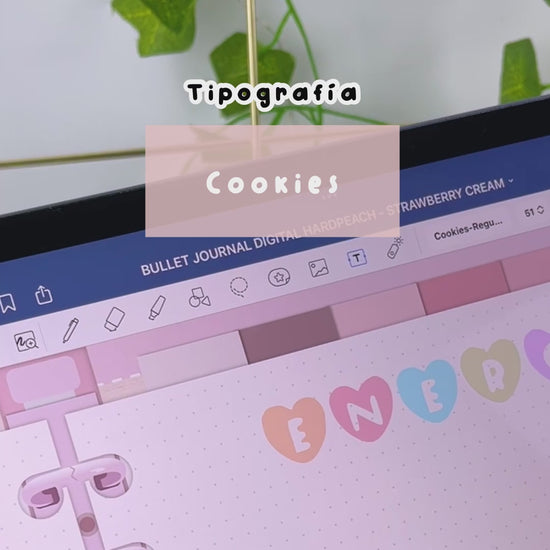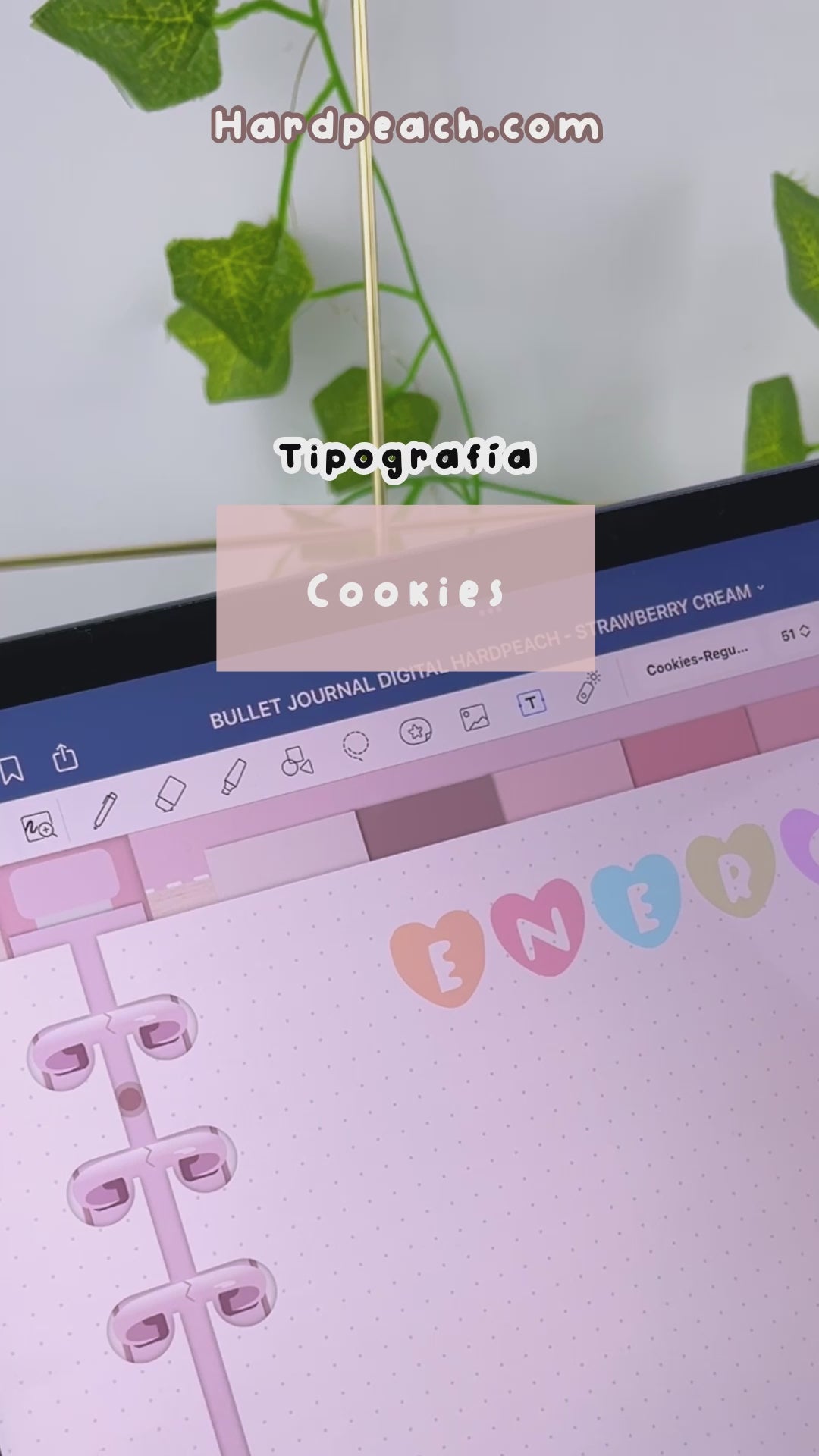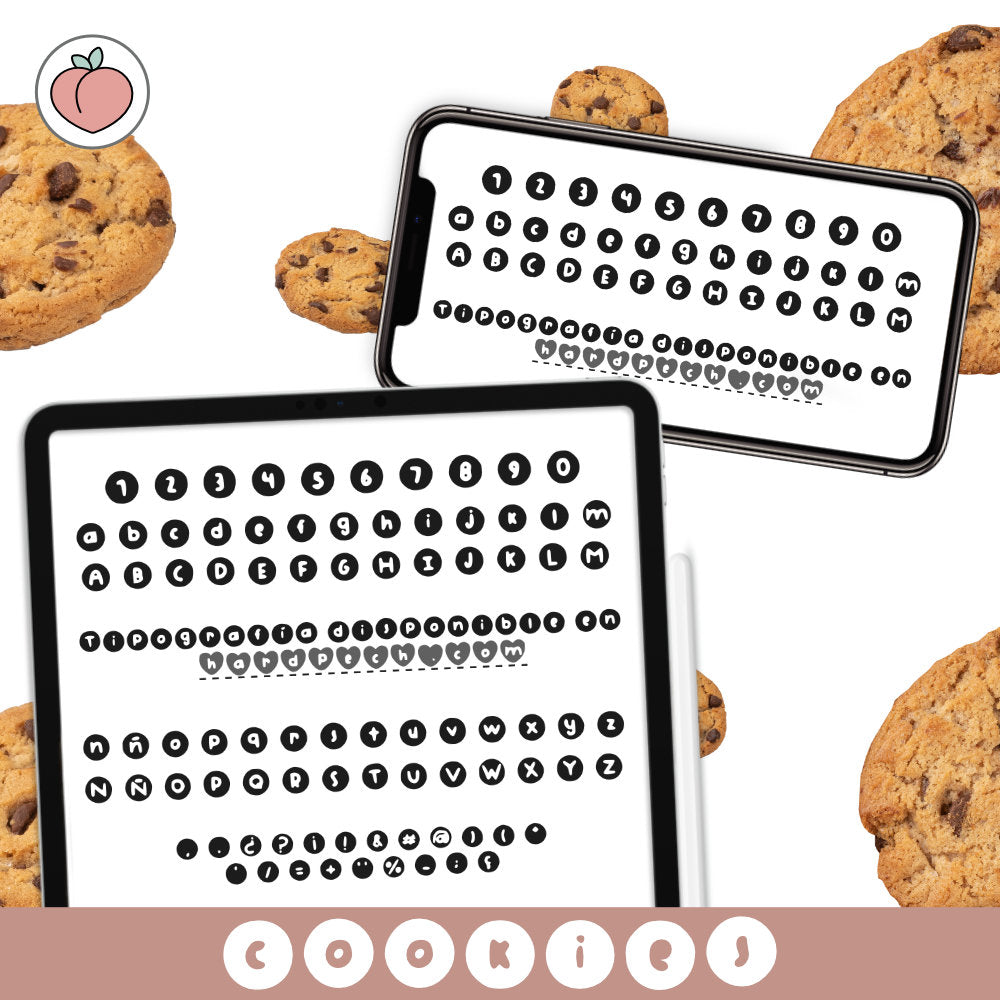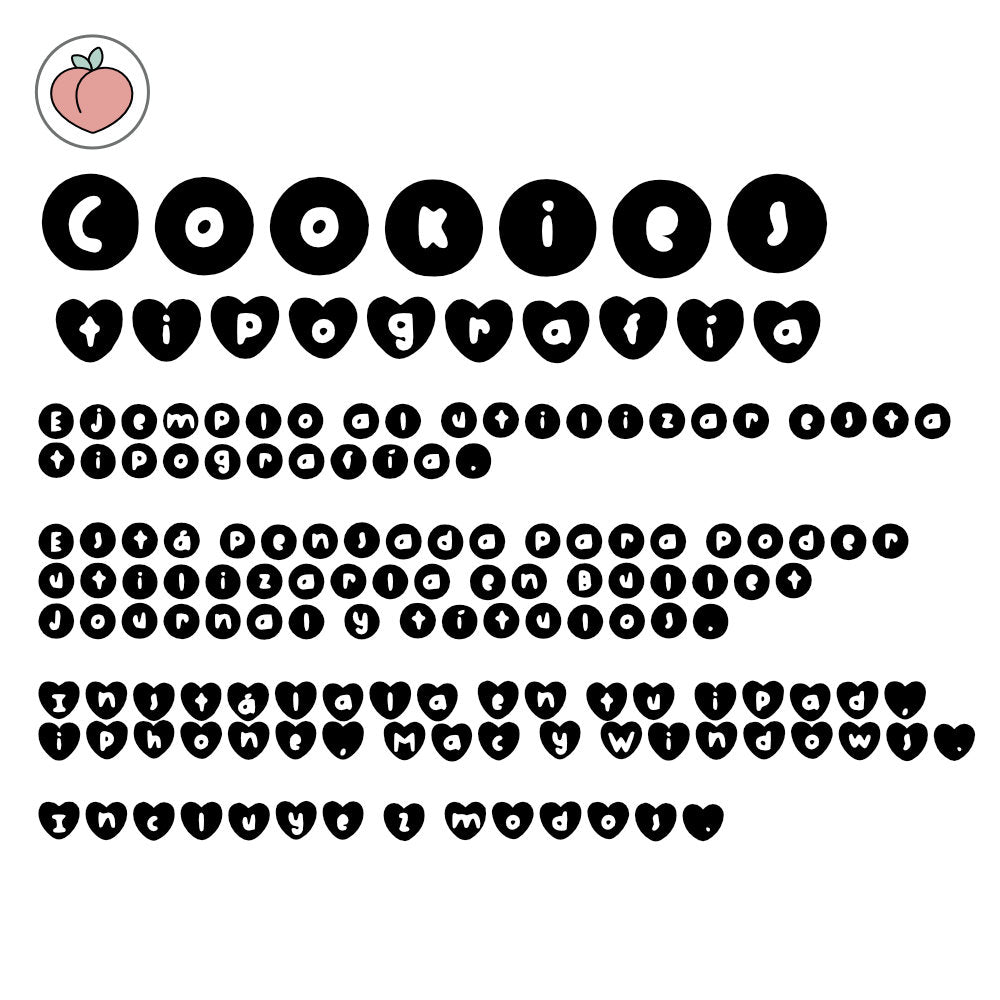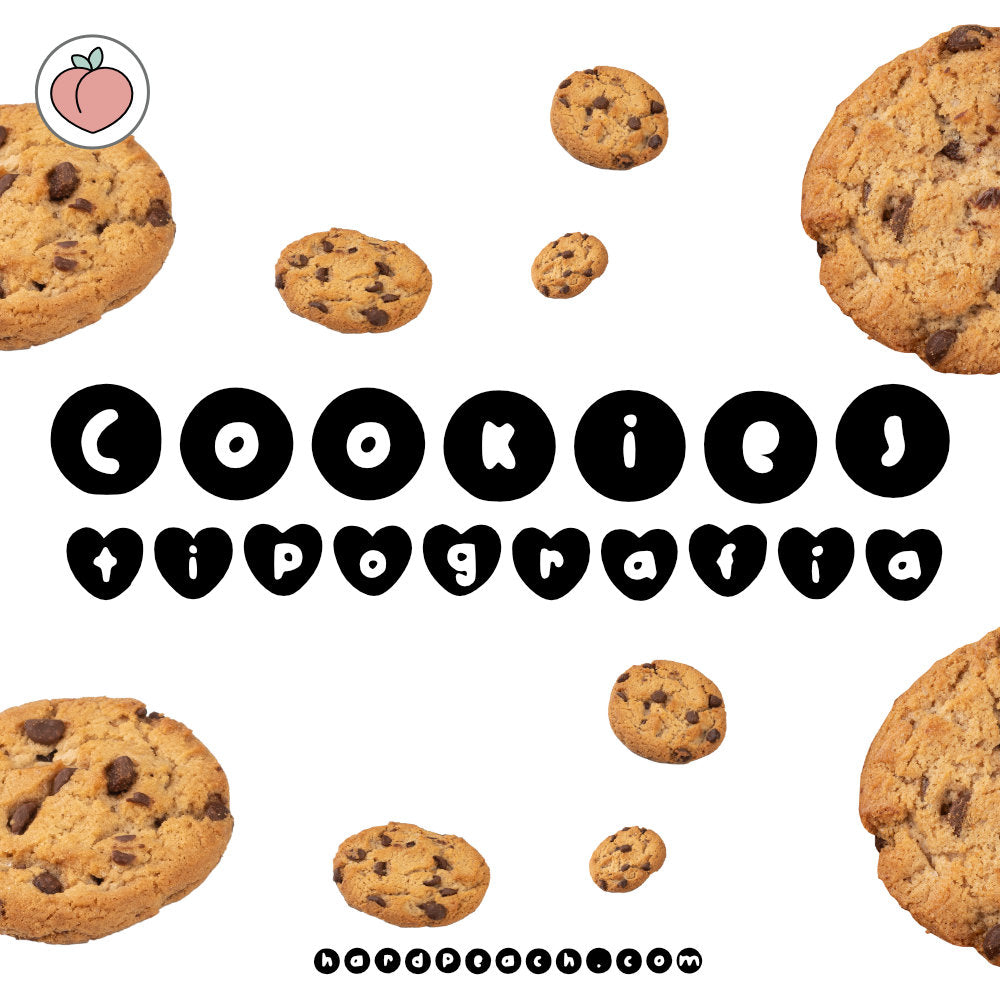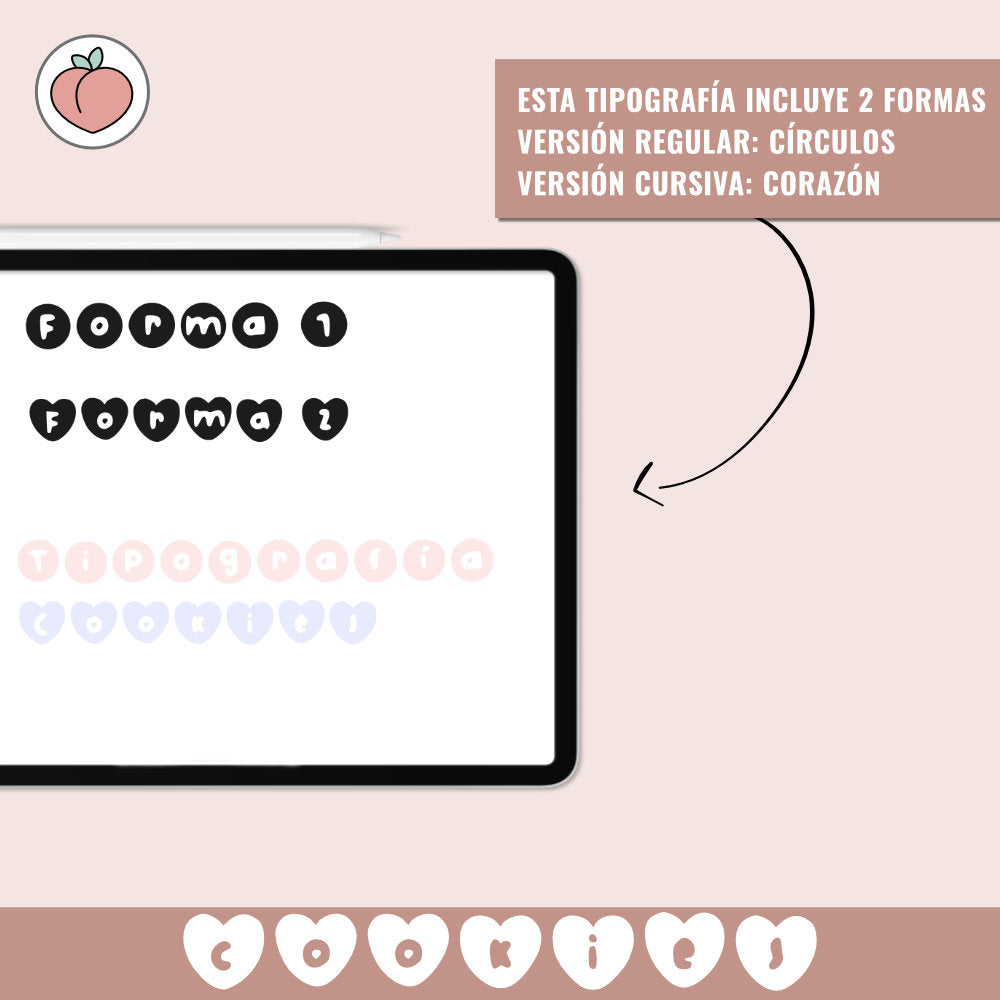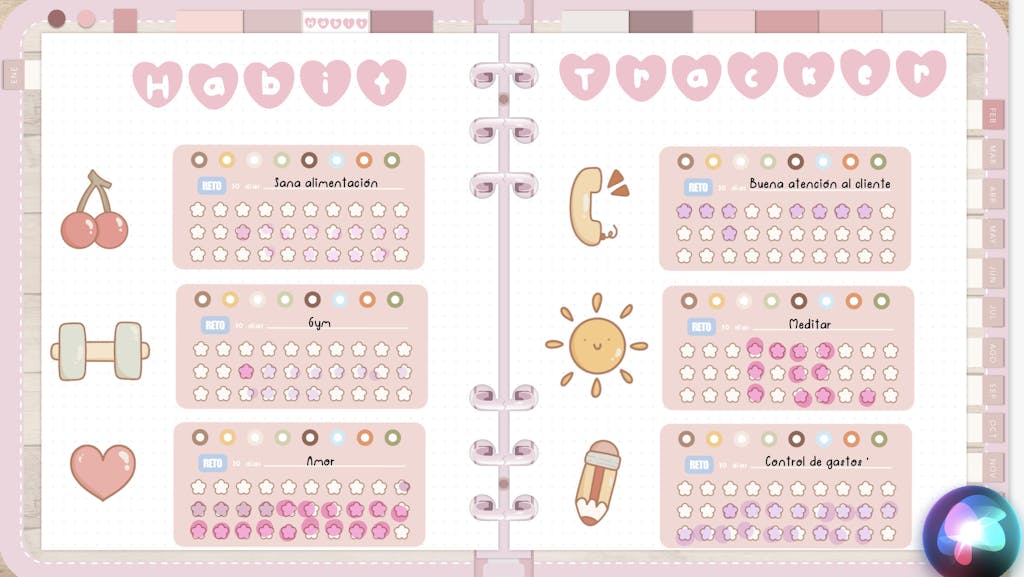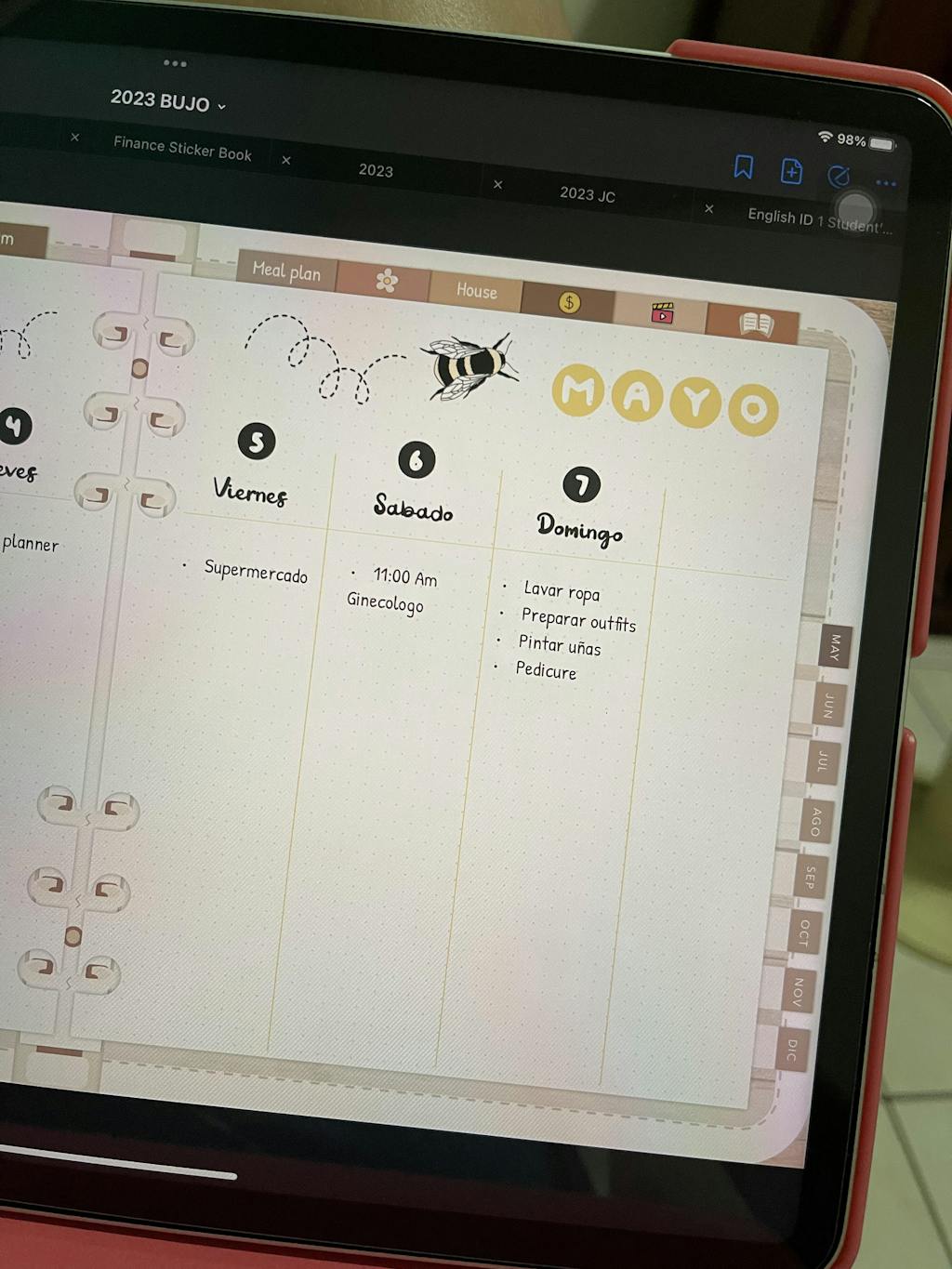
TIPOGRAFÍA COOKIES: Fuente 2 en 1 para títulos, lettering, bullet journals, agendas digitales y proyectos creativos
¡Tipografía 2 en 1 para títulos, Bullet Journal y agendas creativas! ✨
Descubre nuestra tipografía 2 en 1, diseñada para añadir un estilo totalmente único a tus títulos, apuntes, bullet journals, agendas digitales y proyectos creativos. Esta fuente versátil permite escribir con un formato circular o en forma de corazón, dando un toque divertido, moderno y especial a todas tus anotaciones y diseños.
Características principales:
- Dos modos de tipografía: Elige el estilo que mejor se adapte a tu proyecto y personaliza tus textos con facilidad.
- Colores ilimitados: Utiliza la tipografía en el color que necesites para destacar tus títulos, secciones o páginas de tu Bullet Journal y agenda.
- Versatilidad total: Perfecta para apuntes digitales, notas, títulos, encabezados, tarjetas, invitaciones y proyectos de lettering digital.
Ideas de uso:
- Bullet Journals y agendas digitales 🗓️
- Títulos y encabezados para documentos, presentaciones y proyectos ✨
- Notas y apuntes digitales 📝
- Diseños creativos e ilustraciones 🎨
Con esta tipografía 2 en 1, podrás darle vida a tus proyectos y planificaciones, creando un estilo único y atractivo, sin perder funcionalidad ni facilidad de uso. Perfecta para estudiantes, profesionales, amantes del Bullet Journal y cualquier persona que quiera personalizar sus textos digitales con creatividad y estilo.
La tipografía Cookies incluye todos los caracteres principales, mayúsculas, minúsculas, números, vocales con tildes (español), y acentuaciones abiertas (à) y signos. Además, incluye la acentuaciones y las letras ñ y ç.
queda genial para los títulos de apuntes
Adoro esta tipografía para títulos, me encanta que puedes utilizarla en circulitos o en corazones que es mi favorita, le da un super toque a mis títulos o lo que quiero resaltar.
Me encanta para títulos de cuadernos, o para dejar la agenda más llamativa, queda genial.
Es una tipografía muy divertida y para títulos o el bullet journal creo que va genial, la utilizo mucho para esto